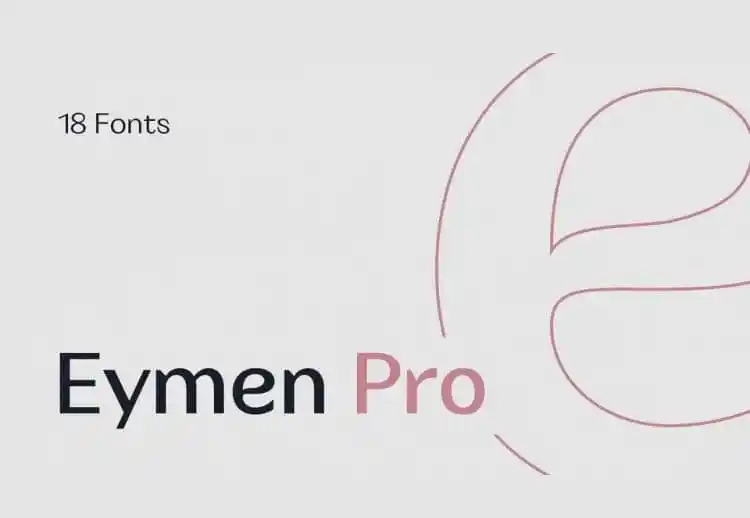
Eymen Pro Sans Serif Font
A Eymen Pro Sans Serif é uma fonte moderna e expressiva desenvolvida por Serdar Öztürk. Apesar de ter sido inicialmente projetada para páginas de texto cool na indústria têxtil, sua família grande a tornou versátil o suficiente para ser usada em múltiplos setores e produtos. A Eymen é uma companheira ideal para seus logos pesados e estéticos. Com seu design clean e moderno, ela oferece um toque único e interessante que se destaca em qualquer layout de gráfica. Sua versão completa proporciona variedade de tamanhos e graus, permitindo que você personalize suas criações para atender às necessidades de cada projeto sem comprometer a sua estética singular. Seja para uma publicação de revista ou um logotipo, Eymen Pro Sans Serif está aqui para ajudar você a criar um design elegante e moderno.